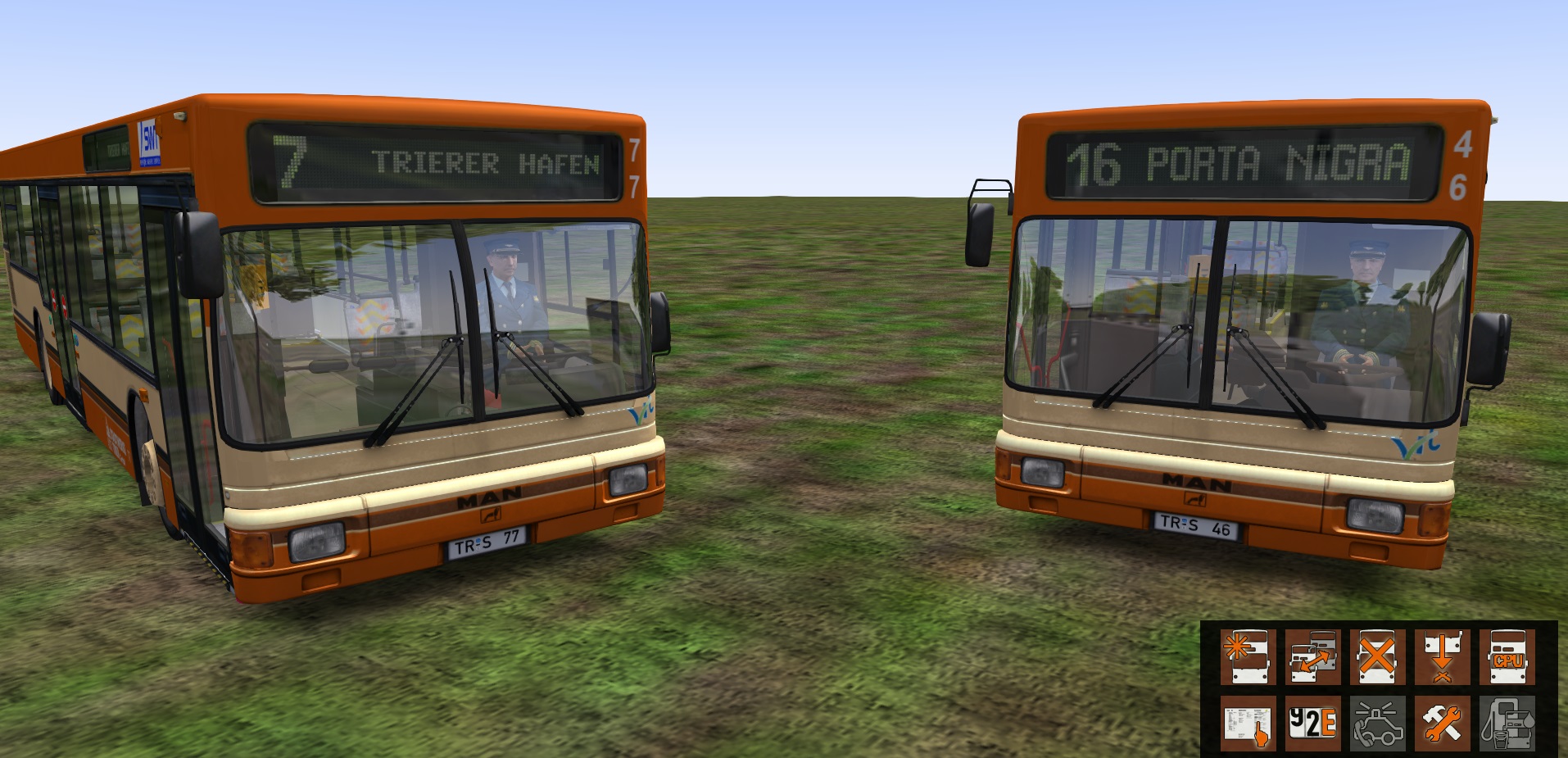
Font für Krueger-Vollmatrix
Krueger-Font aus Trier und Hamburg für die M&R-Vollmatrix.
ich biete hier einen Font für die Krueger-Vollmatrix von M&R an.
Die Schriftart entspricht der der Krueger-Matrixanzeigen aus Trier (ist mit der Hamburger Kruegermatrix vergleichbar).
FEATURES
- originalgetreue Nachbildung der Schriftart von Krueger-Vollmatrixanzeigen (z.B. Trier oder Hamburg)
- ausgeblichene Dots (siehe Bild)
- Sonderanzeigen (Schulbus, Einsatzwagen, Sonderfahrt und Weiße Fläche) zur Einbindung in Hofdateien
HINWEIS